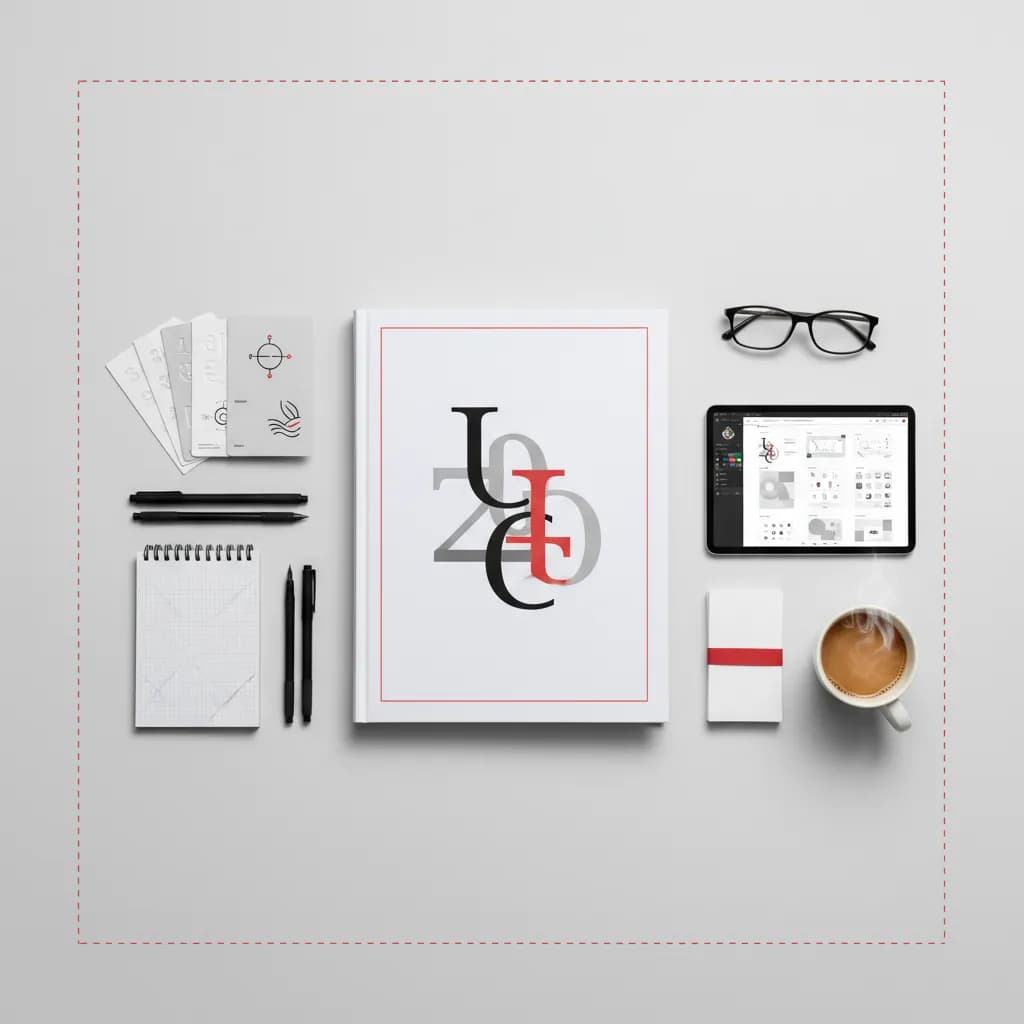
הלוגו הוא הפנים של כל מותג – והפונט שבוחרים לו הוא הקול שלו. בחירה נכונה של פונטים לעיצוב לוגו יכולה להעביר מסר ברור על הזהות, הערכים והאופי של העסק, בעוד בחירה שגויה עלולה לטשטש את המסר ולפגוע באמינות. מעצבים גרפיים יודעים שהטיפוגרפיה בלוגו היא לא רק עניין אסתטי – היא כלי אסטרטגי שמשפיע על הזיהוי המיידי, הבידול מהמתחרים והחיבור הרגשי עם הקהל. במדריך זה נחקור את העקרונות המרכזיים, הטכניקות המעשיות והטעויות הנפוצות בבחירת פונטים לעיצוב לוגו מקצועי.
הפונט בלוגו הוא הרבה יותר מאותיות – הוא נושא משמעויות תרבותיות, רגשיות ופונקציונליות שמשפיעות ישירות על תפיסת המותג. מחקרים בפסיכולוגיה קוגניטיבית מראים שצרכנים יוצרים רושם ראשוני על מותג תוך פחות משתי שניות, והטיפוגרפיה ממלאת תפקיד מרכזי בתהליך זה.
זיהוי מיידי וזיכרון מותג: לוגו עם פונט ייחודי ועקבי נחרת בזיכרון הצרכן מהר יותר. כאשר הפונט מתאים לאישיות המותג – למשל, פונט קלאסי עם אופי מסורתי לעסק עם ותק, או פונט מודרני דינמי לסטארט-אפ טכנולוגי – הזיהוי המיידי משתפר משמעותית.
העברת ערכי מותג: כל משפחת פונטים נושאת עמה קונוטציות ספציפיות. פונטים עם סריפים (Serif) משדרים מסורת, אמינות ויוקרה – מתאימים למשרדי עורכי דין, בתי הוצאה לאור או מותגי אופנה יוקרתיים. פונטים ללא סריפים (Sans-Serif) מעבירים מודרניות, נקיון ויעילות – אידיאליים לחברות טכנולוגיה, סטודיואים לעיצוב או מותגי לייף-סטייל עכשוויים. פונטים סקריפט מעוצבים משדרים אלגנטיות, יצירתיות ואישיות – מושלמים לעסקים באמנות, אירועים או מוצרי פרימיום.
בידול בשוק תחרותי: בתעשיות רוויות, הטיפוגרפיה היא אחד הכלים המרכזיים ליצירת ייחודיות. לוגו עם פונט מותאם אישית או שילוב יצירתי של פונטים קיימים יכול להבדיל מותג מעשרות מתחרים שנראים דומים. לדוגמה, פונט ז'ולייט הוא פונט סקריפט רומנטי בסגנון כתב מכתבים צרפתי – מושלם למותגי חתונות או מוצרי מתנה יוקרתיים שרוצים להדגיש אלגנטיות ורומנטיקה.
בחירת פונטים ללוגו מצריכה איזון עדין בין שיקולים אסתטיים, פונקציונליים ואסטרטגיים. הנה העקרונות המרכזיים שכל מעצב צריך לשקול:
1. קריאות בכל גודל ומדיום
הלוגו צריך להיות קריא מרחוק על שלט חוצות ובגודל זעיר על כרטיס ביקור. פונטים עם פרטים עדינים מדי עלולים להיעלם בגדלים קטנים, בעוד פונטים כבדים מדי עלולים להיראות מסורבלים בגדלים גדולים. בדקו את הלוגו בגדלים שונים – מ-16 פיקסלים (גודל favicon) ועד 2 מטר (שלט חוצות). פונטים ללא סריפים עם משקל בינוני נוטים לעבוד טוב יותר בטווח רחב של גדלים.
2. התאמה לאישיות המותג
הפונט צריך לשקף את האופי הייחודי של המותג. מותג צעיר ודינמי ייהנה מפונט עם זוויות חדות ומשקל מודרני, בעוד מותג מסורתי ומבוסס יתאים יותר לפונט קלאסי עם אופי יציב. לדוגמה, פונט לאבלי הוא פונט כותרות דומיננטי וסוחף שעוצב עם עט המברשת – מתאים למותגים שרוצים להדגיש אנרגיה, יצירתיות ואופי בולט.
3. ייחודיות ללא פשרות
הימנעו מפונטים שכיחים מדי שמשמשים אלפי עסקים. פונטים כמו Arial, Helvetica או Times New Roman הם קריאים ומקצועיים, אבל הם לא יעזרו למותג להתבלט. חפשו פונטים עם אופי ייחודי או שקלו התאמה אישית – שינוי קל באות אחת או בפרופורציות יכול להפוך פונט סטנדרטי לייחודי. טיפוגרפיה מותאמת אישית היא השקעה שמשתלמת לטווח ארוך.
גם מעצבים מנוסים נתקלים לפעמים במלכודות טיפוגרפיות שפוגעות ביעילות הלוגו. הנה הטעויות השכיחות ביותר ואיך להימנע מהן:
שימוש ביותר מדי פונטים: שילוב של שלושה פונטים או יותר בלוגו אחד יוצר בלגן ויזואלי ומחליש את המסר. הכלל המקובל: פונט אחד חזק עדיף על שניים חלשים. אם אתם משלבים שני פונטים, ודאו שהם משלימים זה את זה – למשל, פונט Serif לשם המותג ופונט Sans-Serif לתת-כותרת. הקונטרסט צריך להיות ברור: אם שני הפונטים דומים מדי, השילוב נראה כמו טעות ולא כמו החלטה מכוונת.
התעלמות מקריאות בעברית: פונטים שתוכננו במקור לאנגלית לא תמיד עובדים טוב בעברית. האותיות העבריות דורשות יחס גובה-רוחב שונה, וניקוד (אם נדרש) צריך מרווח אנכי מספיק. בדקו את הפונט עם טקסט עברי ממשי – לא רק עם שם המותג, אלא גם עם משפט שלם כדי לראות איך הוא מתנהג. למותרגים עם טיפוגרפיה איכותית בעברית, כדאי לבדוק פונטים שפותחו במיוחד לשפה – למשל, פונט אספרסו הוא פונט Sans-Serif דו-לשוני עם ניקוד, שעוצב במיוחד לעבודה חלקה בעברית ובאנגלית.
מעקב אחר טרנדים במקום זהות מותג: פונטים טרנדיים משתנים כל כמה שנים – מה שנראה חדשני היום עלול להיראות מיושן תוך שנתיים. לוגו צריך לעמוד במבחן הזמן. במקום לרדוף אחרי הטרנד האחרון, התמקדו בפונט שמשקף את הערכים הליבה של המותג. פונט קלאסי עם עדכון עדין (כמו משקל מודרני או מרווחים מותאמים) יישאר רלוונטי הרבה יותר זמן מפונט "חם" שכולם משתמשים בו השנה.
התעלמות מבדיקות הדפסה: לוגו שנראה מעולה על מסך יכול להיכשל בהדפסה. פונטים עם קווים דקים מדי עלולים להיעלם בהדפסה על חומרים מסוימים, ופרטים עדינים יכולים להתמזג. תמיד בדקו את הלוגו בהדפסה פיזית – על נייר רגיל, על כרטיס ביקור ועל חומרים מיוחדים (בד, פלסטיק) אם רלוונטי לעסק. Google Fonts מציעה כלי תצוגה מקדימה שעוזר לבדוק איך פונטים נראים בגדלים שונים.
עכשיו שהבנו את העקרונות והטעויות, הנה תהליך שלב-אחר-שלב שיעזור לכם לבחור את הפונט המושלם:
שלב 1: הגדירו את אישיות המותג
לפני שאתם פוקחים תוכנת עיצוב, השקיעו זמן בהגדרת האישיות. רשמו 3-5 תארים שמתארים את המותג: מודרני? קלאסי? משחקי? רציני? יוקרתי? נגיש? התארים האלה יהפכו למצפן שלכם בבחירת הפונט. לדוגמה, אם המותג הוא "מסורתי, אמין ומקצועי" – תחפשו פונטים עם סריפים, משקל בינוני ופרופורציות קלאסיות.
שלב 2: צרו short-list של 5-7 פונטים
חפשו בספריות פונטים (כמו Adobe Fonts או Lia Fonts) ובחרו מספר מועמדים. התמקדו בפונטים שמתאימים לתארים שהגדרתם. אל תתאהבו בפונט רק כי הוא יפה – שאלו את עצמכם אם הוא משדר את המסר הנכון. לדוגמה, פונט יפני הוא פונט מורכב בהשראת קליגרפיה יפנית – מתאים למותגים שרוצים להדגיש אומנות, דיוק ותרבות.
שלב 3: בצעו בדיקות מעשיות
עצבו את שם המותג בכל אחד מהפונטים ברשימה. בדקו אותם בשלושה גדלים: זעיר (50 פיקסלים), רגיל (200 פיקסלים) וגדול (800 פיקסלים). בדקו אותם על רקעים שונים – לבן, שחור וצבע המותג. הדפיסו אותם בגודל כרטיס ביקור. הפונטים שעוברים את כל הבדיקות האלה ממשיכים לשלב הבא.
שלב 4: קבלו משוב ממקורות מגוונים
הראו את הגרסאות הסופיות (2-3 מועמדים) לאנשים מקהל היעד, לעמיתים מקצועיים ולבעלי העניין בפרויקט. שאלו שאלות ספציפיות: "איזה תארים עולים לכם בראש כשאתם רואים את הלוגו?" אם התשובות תואמות את האישיות שהגדרתם – אתם על המסלול הנכון.
צ'ק-ליסט: האם בחרתם את הפונט הנכון?
התשובה תלויה בתקציב ובמטרות. פונטים חינמיים מספקים נקודת התחלה טובה, אבל לעתים קרובות חסרים להם משקלים נוספים או תמיכה מלאה בעברית. פונט מקצועי מציע גמישות רבה יותר, משקלים מרובים ותמיכה טכנית. אם המותג שלכם מכוון לטווח ארוך ותדמית פרימיום – השקעה בפונט איכותי היא החלטה נבונה. חשוב גם לבדוק את תנאי הרישיון – פונטים חינמיים לא תמיד מתירים שימוש מסחרי בלוגו.
כן, אבל בזהירות. שילוב מוצלח דורש קונטרסט ברור – למשל, פונט Serif עבה לשם המותג ופונט Sans-Serif דק לתת-כותרת. הכלל: אם שני הפונטים דומים מדי, השילוב ייראה כמו טעות. אם הם שונים מדי, הלוגו ייראה לא מאוזן. התחילו עם פונט אחד חזק – תמיד אפשר להוסיף שני בעתיד אם יש צורך ברור.
בדקו את הפונט עם טקסט עברי ממשי – לא רק עם שם המותג. כתבו משפט שלם ובדקו אם המרווחים בין האותיות טבעיים, אם יש תמיכה בניקוד (אם נדרש), ואם האותיות הסופיות (כמו ם, ן, ץ) מעוצבות היטב. פונטים שתוכננו במקור לאנגלית לעתים מציגים בעיות בעברית – אותיות צרות מדי, מרווחים לא אחידים או יחס גובה-רוחב לא מאוזן. בחרו פונטים שפותחו עם מחשבה על השפה העברית.
בחירת פונטים לעיצוב לוגו היא החלטה אסטרטגית שמשפיעה על הזיהוי, האמינות והבידול של המותג. הפונט הנכון משדר את אישיות המותג, נשאר קריא בכל גודל ומדיום, ועומד במבחן הזמן. הימנעו מטעויות נפוצות כמו שימוש ביותר מדי פונטים, מעקב עיוור אחרי טרנדים או התעלמות מבדיקות הדפסה פיזיות.
עקבו אחר התהליך המעשי: הגדירו את אישיות המותג, צרו short-list של מועמדים, בצעו בדיקות מעמיקות וקבלו משוב ממקורות מגוונים. זכרו שפונטים לעיצוב לוגו הם לא רק עניין של יופי – הם כלי תקשורת שמעביר מסרים ערכיים, רגשיים ופונקציונליים. השקיעו זמן בבחירה הנכונה, והלוגו שלכם יהפוך לנכס מותגי חזק שמלווה את העסק שנים קדימה.